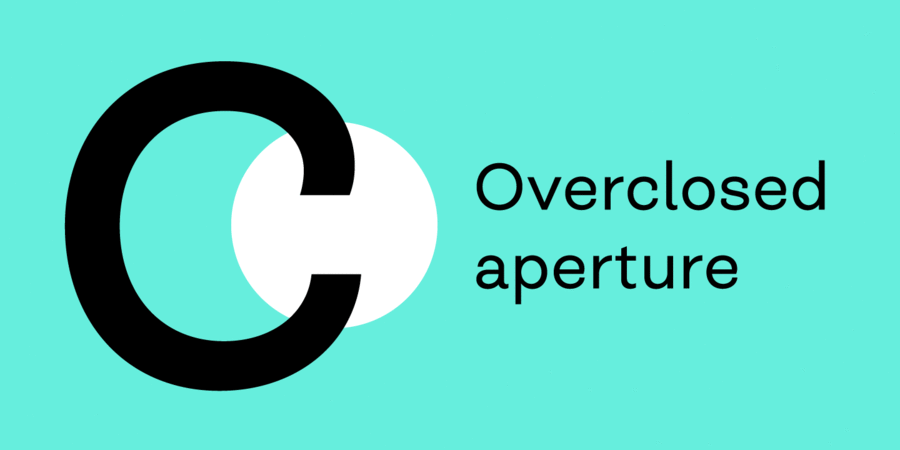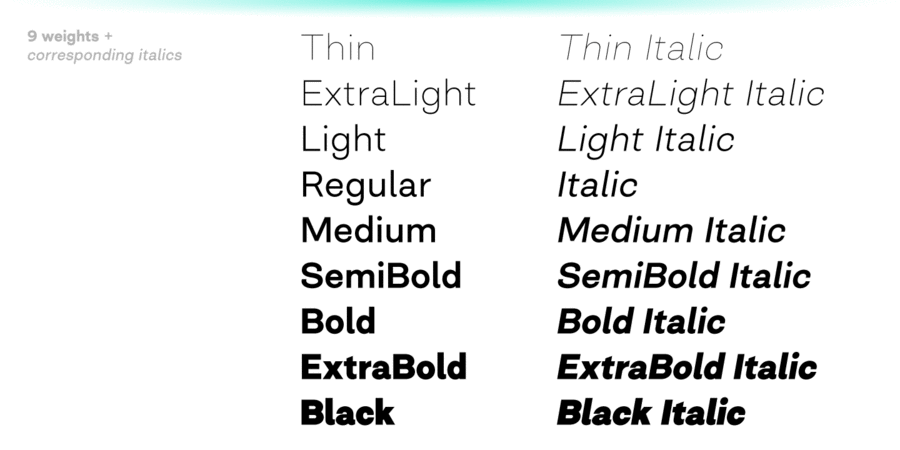
Більш компактна версія шрифту Closer. Його можна охарактеризувати як швейцарський гротеск з закритою апертурою. Шрифт має гуманістичні форми, він виглядає менш прісним, але все ще відносно нейтральним.
Closer складається з 9 накреслень (в цілому 18 стилів), має розширену підтримку мов, включно з кирилицею, і володіє широкими можливостями з 7 стилістичними наборами для змішування і знаходження найкращих поєднань.
Шрифт розробив Андрій Константинов у 2019 році.
Асоціації з сімейством шрифтів Closer TextОсобистість і характер гарнітури:
лаконічний, міський, якісний, спокійний, сучасний, модний, холодний, тонкий, легкий, ясний, чистий, невагомий, прозорий, гладенький, крихкий, дротяний, гнучкий, оригінальний, добрий, приємний, делікатний, прохолодний, культурний, багатий, ніжний, затишний, неоновий, інтимний, мирний, комфортний, скляний, свіжий, стабільний, статичний, стійкий, глобалізований, глобалістічний, технічний, впевнений, надійний, спортивний, важливий, переконливий, наполегливий, строковий, потужний, сильний, авторитетний, помітний, важкий, індустріальний, крутий
дизайн, чистота, гігієна, шампунь, дієта, краса, туалетна вода, косметика, мода, АСМР, парфумерія, лосьйон, Місто, медицина, здоров'я, екологія, одяг, йога, вода, ліки, торгівля, Локдаун, захист, тренажери, верстат, машинобудування, промисловість, енергетика, електростанція, вантажоперевезення, вантажівка, спорт, інструмент, мотор, двигун, шоу, телебачення, металургія, Доставка Гарнітура має ознаки стилів: